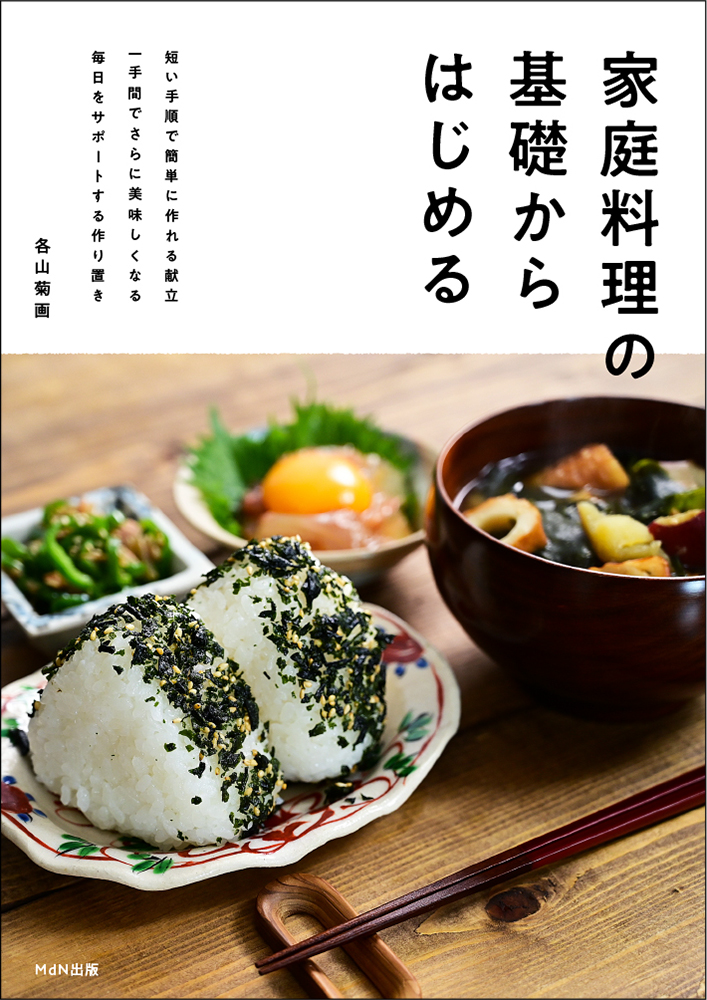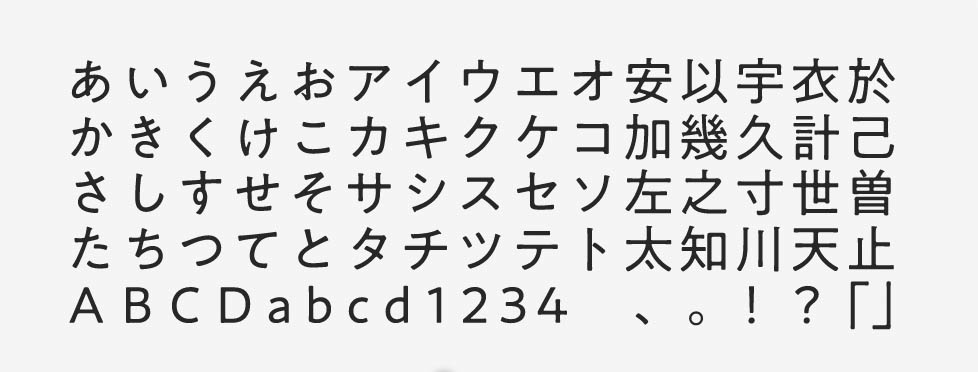
「A1ゴシック」について
2017年に登場したA1ゴシックは、先行してリリースされて人気を博していたA1明朝の基本となる骨格を参照しながら生み出されました。開発時、9,345文字に及ぶ全ての原図は手書きで作られています。一般的にゴシック体は力強いイメージですが、A1ゴシックが目指したのは「温かみのあるゴシック体」です。モリサワの代表的なモダンスタイルのゴシック体「新ゴ」と比べると、「A1ゴシック」はふところが狭く、有機的な骨格であるオールドスタイルに分類されます。
「A1ゴシック」の特徴
「A1ゴシック」の特徴として、温もりを感じさせるポイントの1つが、線画の交差する部分に加えられた墨だまりです。親しみが持てる暖かい雰囲気がしますね。エレメントの先端の角はわずかに丸みを帯びており、ゴシック体でありながらも優しさを感じさせます。
A1明朝と合わせて使いやすいフォントとして開発されているため、組み合わせたときの相性は抜群です。A1ゴシックは、L・R・M・Bという4つのウエイトで展開されています。
ほのかに古風な雰囲気で、日頃から頻繁に活用している大好きなフォントです。角ゴシック体と丸ゴシック体の間を行くような愛らしさを感じます。個性が強すぎないように見えながらも確実にあり、それこそがA1ゴシックの個性、といった不思議な魅力のフォントです。